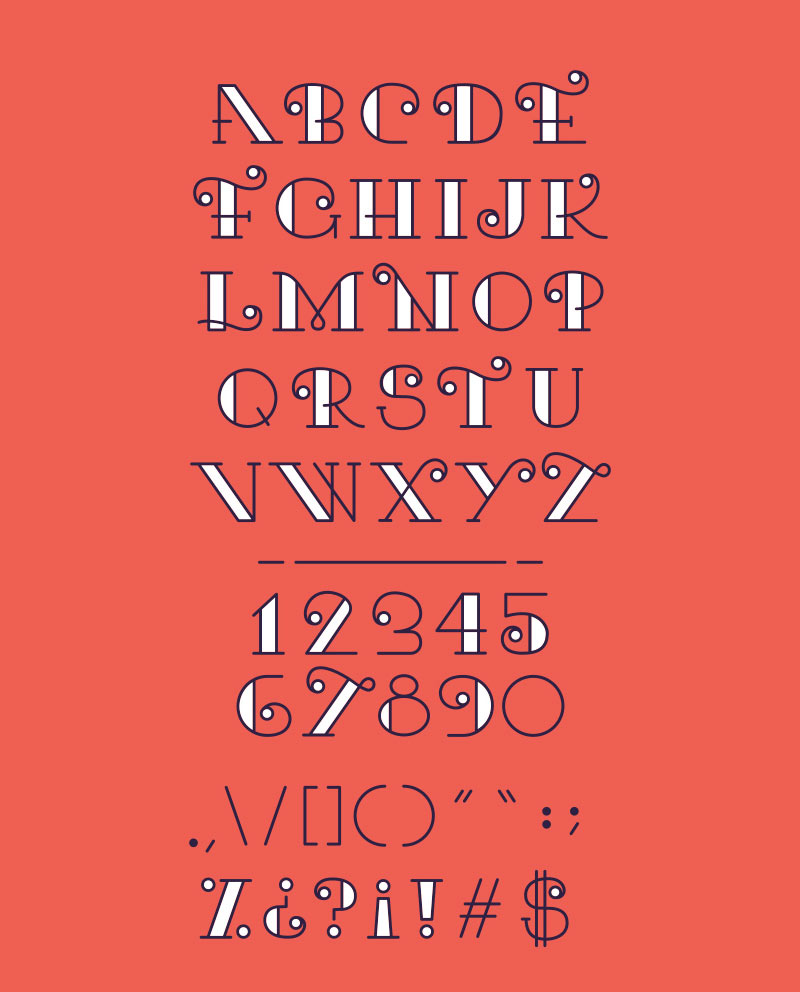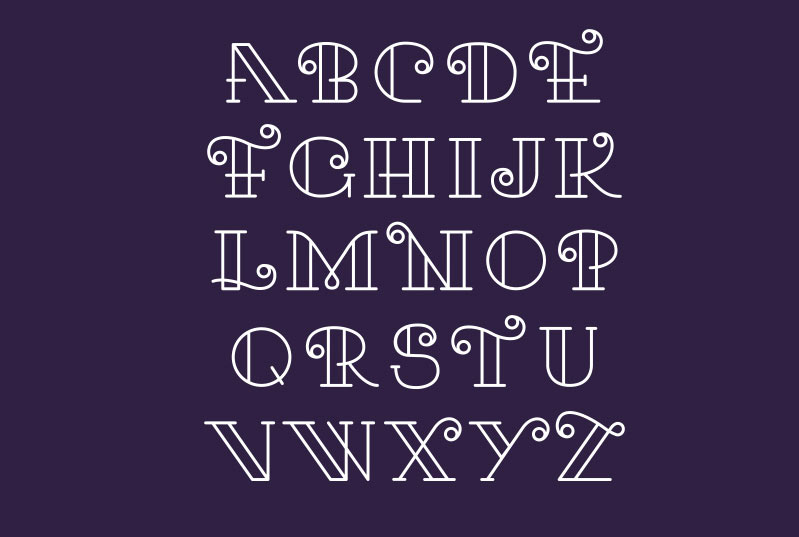
El diseñador mexicano Javier Rivero nos trae la fuente tipográfica para la 26 edición de nuestro especial dedicados a las fuentes. Kari, es una fuente inspirada en los años 50’s, los tatuajes y el mar. Ya podéis descargar esta estupenda y bonita fuente más abajo.